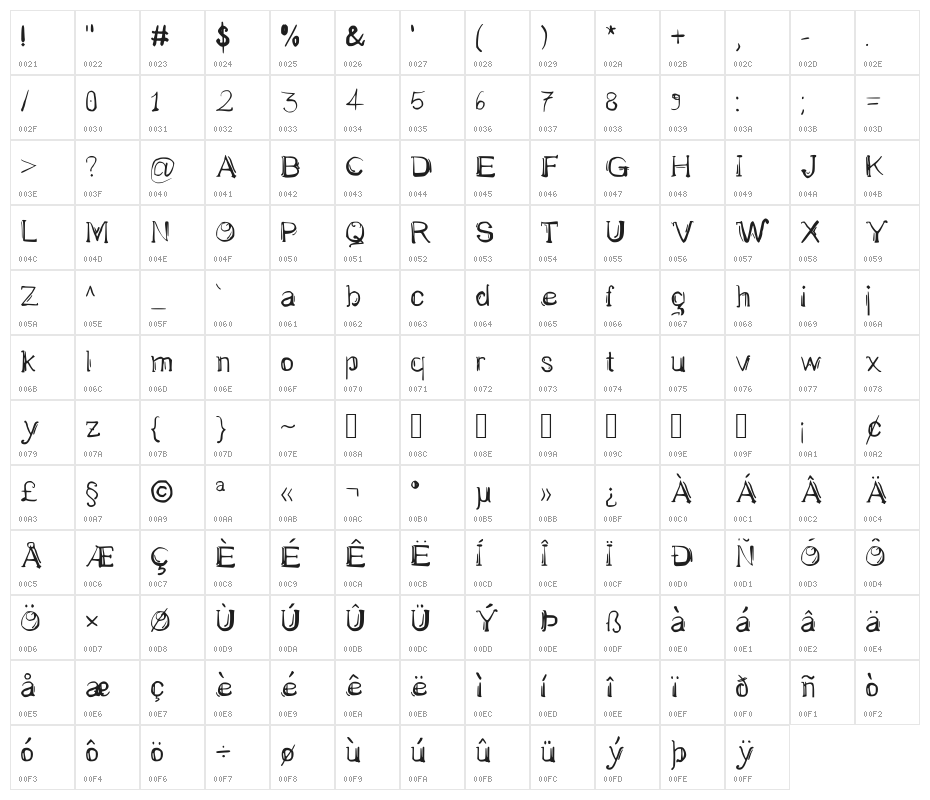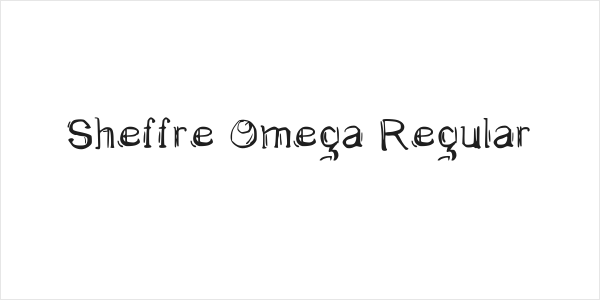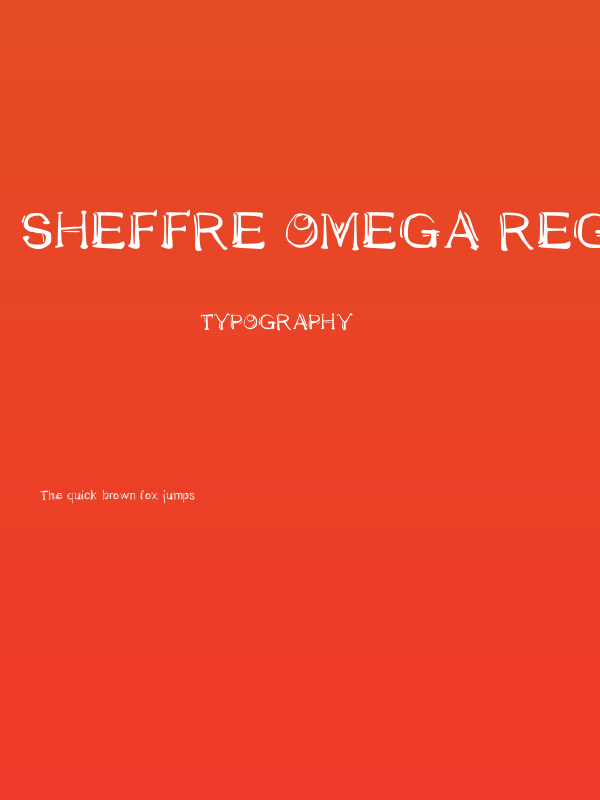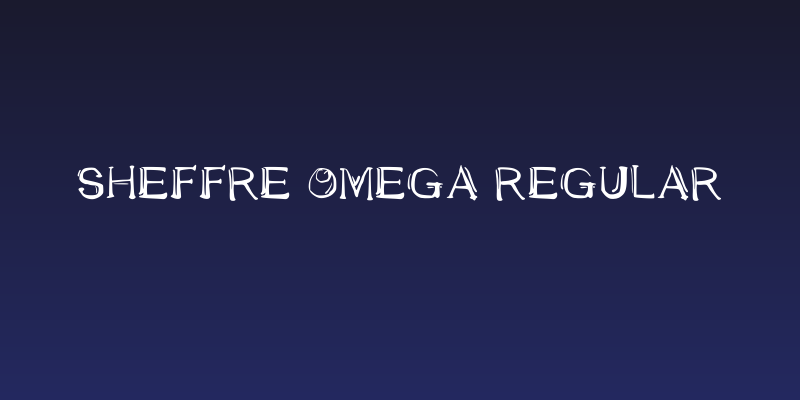
Sheffre Omega Regular Font
| Proiecte propuse | Ideal for creative projects such as posters, album covers, branding for artistic ventures, or any design requiring a distinctive and eye-catching typeface. |